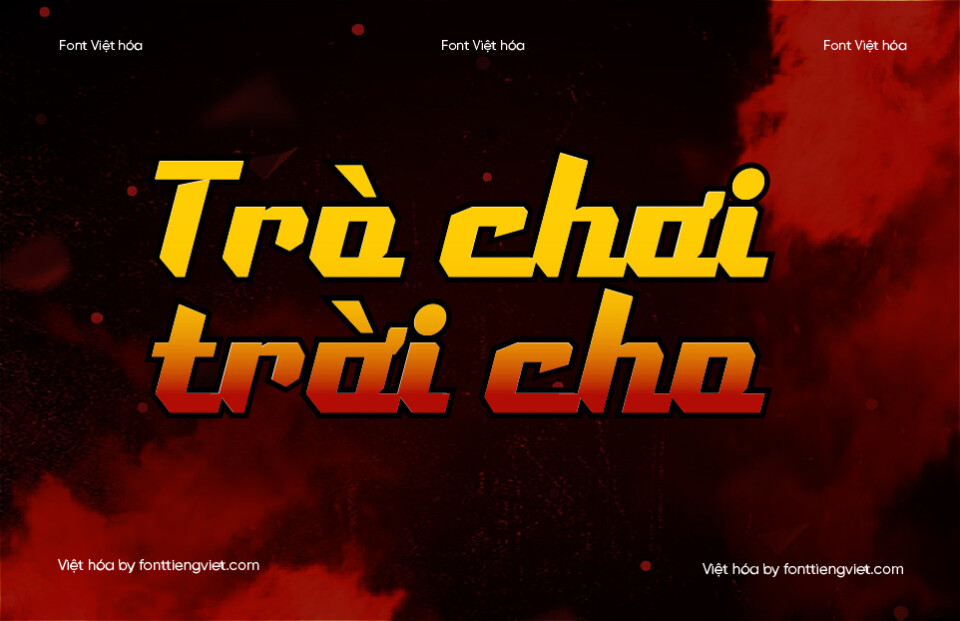
Font Việt hóa 1FTV Racing Games
Giới thiệu về bộ Font Việt hóa 1FTV Racing Games
Trong thế giới đồ họa hiện đại, việc tìm kiếm một bộ Font Miễn Phí chất lượng để truyền tải sự mạnh mẽ và tốc độ là điều không hề dễ dàng. Font Việt hóa 1FTV Racing Games nổi lên như một lựa chọn hàng đầu dành cho các bạn học sinh và nhà thiết kế yêu thích phong cách thể thao điện tử. Bộ phông chữ này được tối ưu hóa hoàn toàn cho tiếng Việt, giúp bạn dễ dàng trình bày nội dung mà không lo lỗi hiển thị hay thiếu dấu.
Đặc điểm nổi bật của Font Việt hóa 1FTV Racing Games
Phong cách thiết kế hiện đại
Đúng như tên gọi, Font Việt hóa 1FTV Racing Games mang trong mình những đường nét góc cạnh, dứt khoát và đầy tính động lực. Kiểu dáng chữ hơi nghiêng về phía trước tạo cảm giác chuyển động không ngừng, rất phù hợp cho các tiêu đề lớn hoặc logo thương hiệu. Sự hài hòa giữa các nét thanh và nét đậm giúp chữ giữ được độ rõ nét ngay cả khi hiển thị trên màn hình điện thoại hay máy tính.
Tính ứng dụng cao trong học đường
Không chỉ dùng cho game, bộ font này còn cực kỳ hữu ích trong các bài thuyết trình, thiết kế áo lớp hoặc làm poster cho các sự kiện thể thao trường học. Nhờ bảng mã đã được Việt hóa chỉn chu, các em học sinh có thể tự do sáng tạo những khẩu hiệu đầy cá tính mà vẫn giữ được sự chuyên nghiệp và tinh tế trong từng con chữ.
Để đạt hiệu quả thẩm mỹ tốt nhất, bạn nên sử dụng font này cho các đề mục chính thay vì các đoạn văn bản dài. Kết hợp với các tông màu rực rỡ như đỏ, xanh neon hoặc vàng sẽ làm nổi bật tính chất “racing” đặc trưng. Đây là món quà tuyệt vời từ Font Miễn Phí, Font Việt Hóa, Font Việt hóa 1FTV Racing Games dành cho cộng đồng sáng tạo. Hãy trải nghiệm ngay Font Việt hóa 1FTV Racing Games để làm mới các dự án của mình.